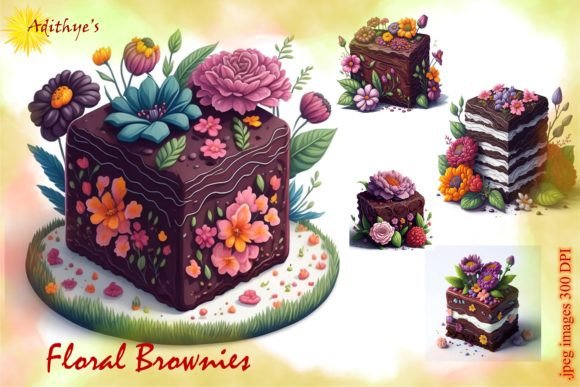
Floral Brownies
Trouver les bons éléments de conception peut être un défi, mais Floral Brownies propose une collection exceptionnelle qui rehausse instantanément votre travail.